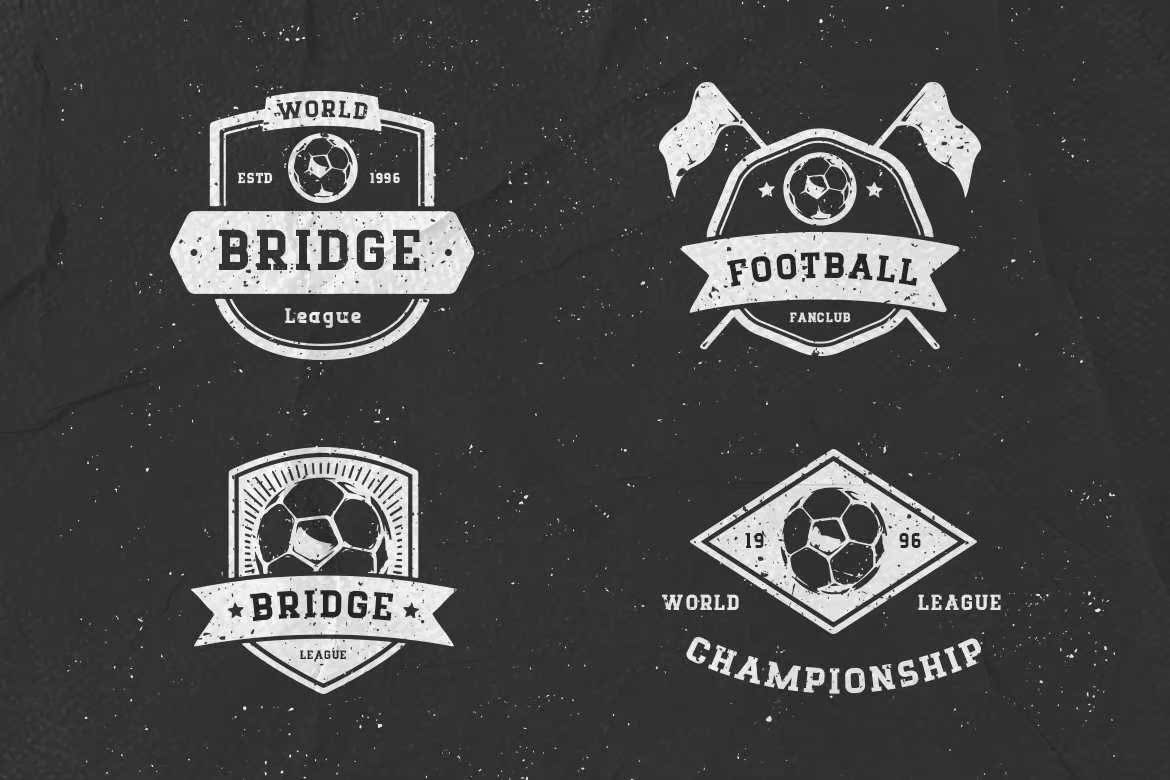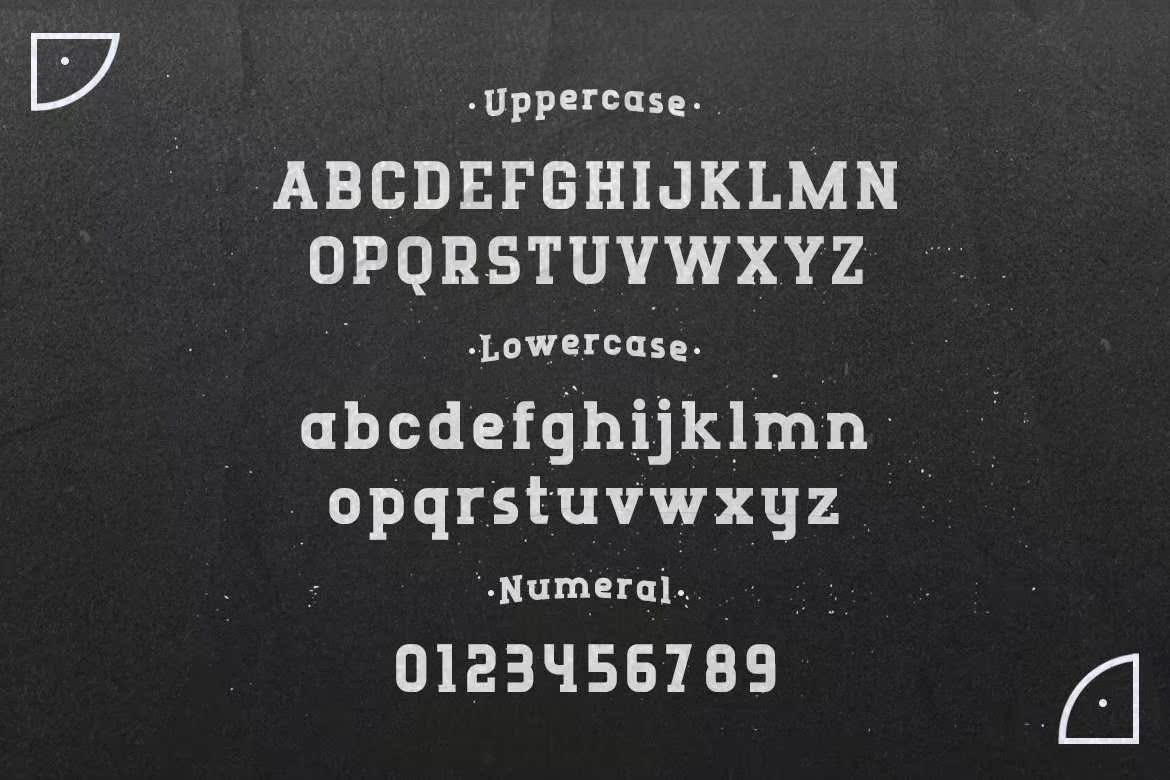
Runboy是一款结实的Slabserffort字体。它的字体排列整齐美观,无论是在正式设计还是非正式设计中都会脱颖而出。非常适合于头饰或徽标、夹克、,PorterFindsits采用19世纪中期风格的字体,使用大量的标签和辛勤工作的外观。全版下载:Runboy是一款强大的Slabersperffort。由于其整洁美观的文字排列,这款字体在正式和非正式设计中都会显得非常出色。非常适合于头饰或徽标、夹克、,PorterFind采用19世纪中期的样式,使用大量的LabSerif和辛勤工作的外观。完整版本下载: